12月,你好,在2021年余额仅剩3开头的时间里,字语坊字库又再接再厉,马不停蹄的为大家上线了两款新品字体。接下来我们带大家揭开这两款字体的面纱。
第一款:字语相思体
字语相思体这款字既有坚硬刚强的感觉,又有圆润舒适的感觉,另外添加了少量的连笔。适用于动漫用字、书刊、品牌广告和产品包装设计,以及社交网络的个性化用字。
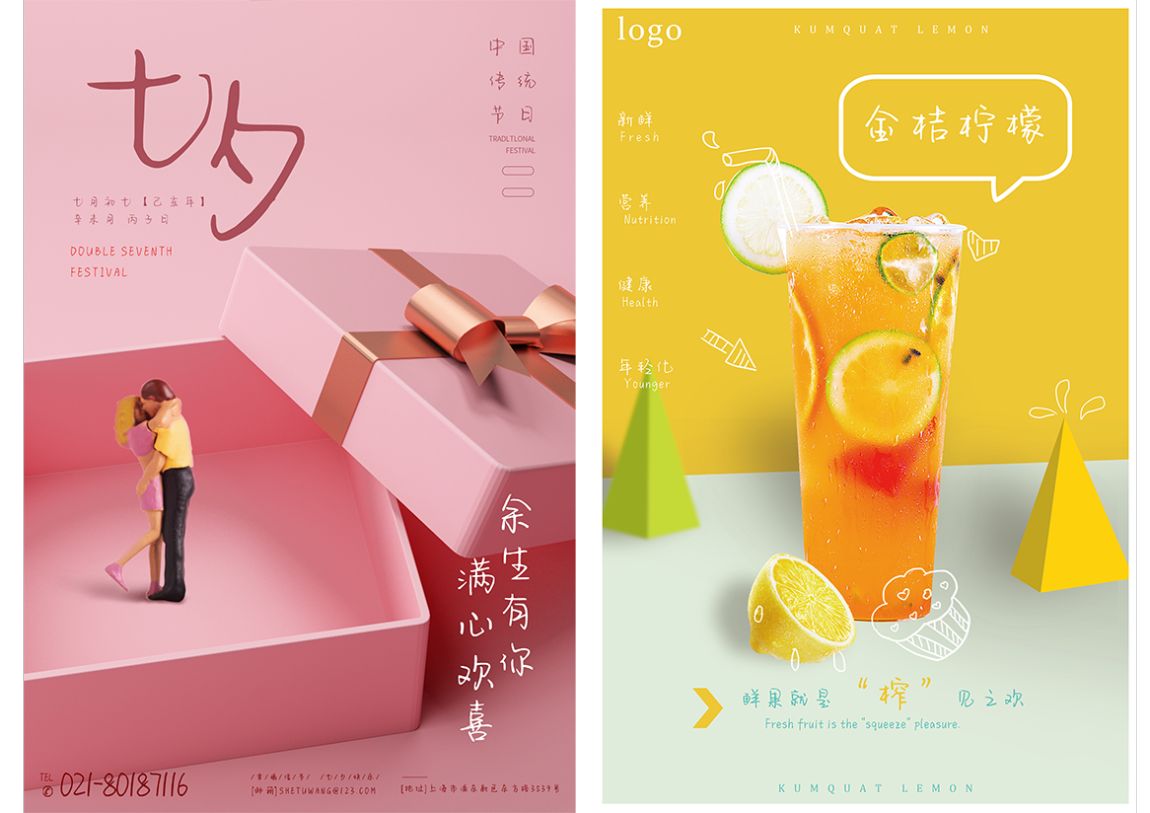
第二款:字语素笺体
字语素笺体这款字体笔画质朴,结构简单个性,转折处方中带圆,趣味十足。适用于动漫用字、少儿类书刊、品牌广告和产品包装设计,以及社交网络的个性化用字。